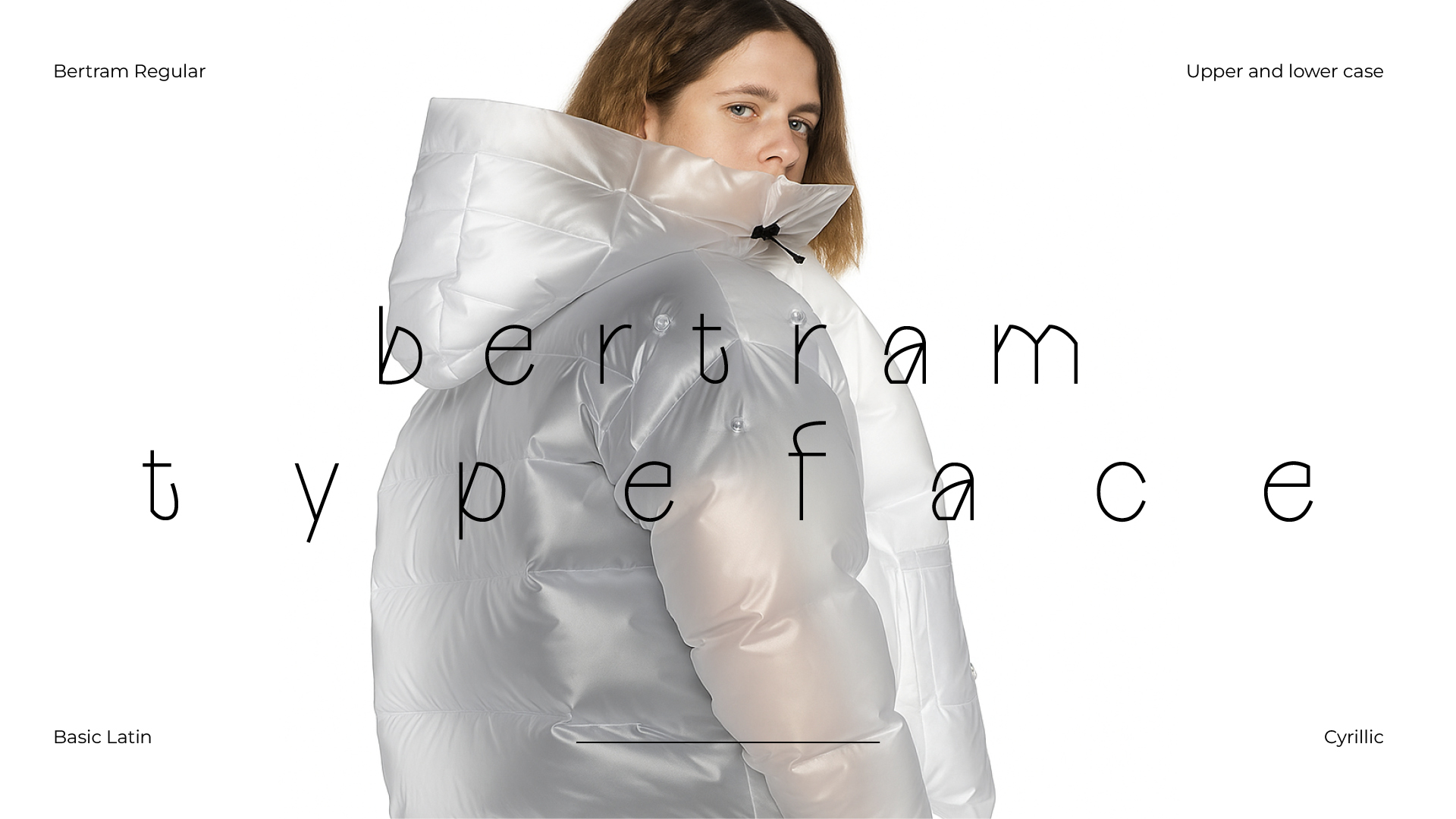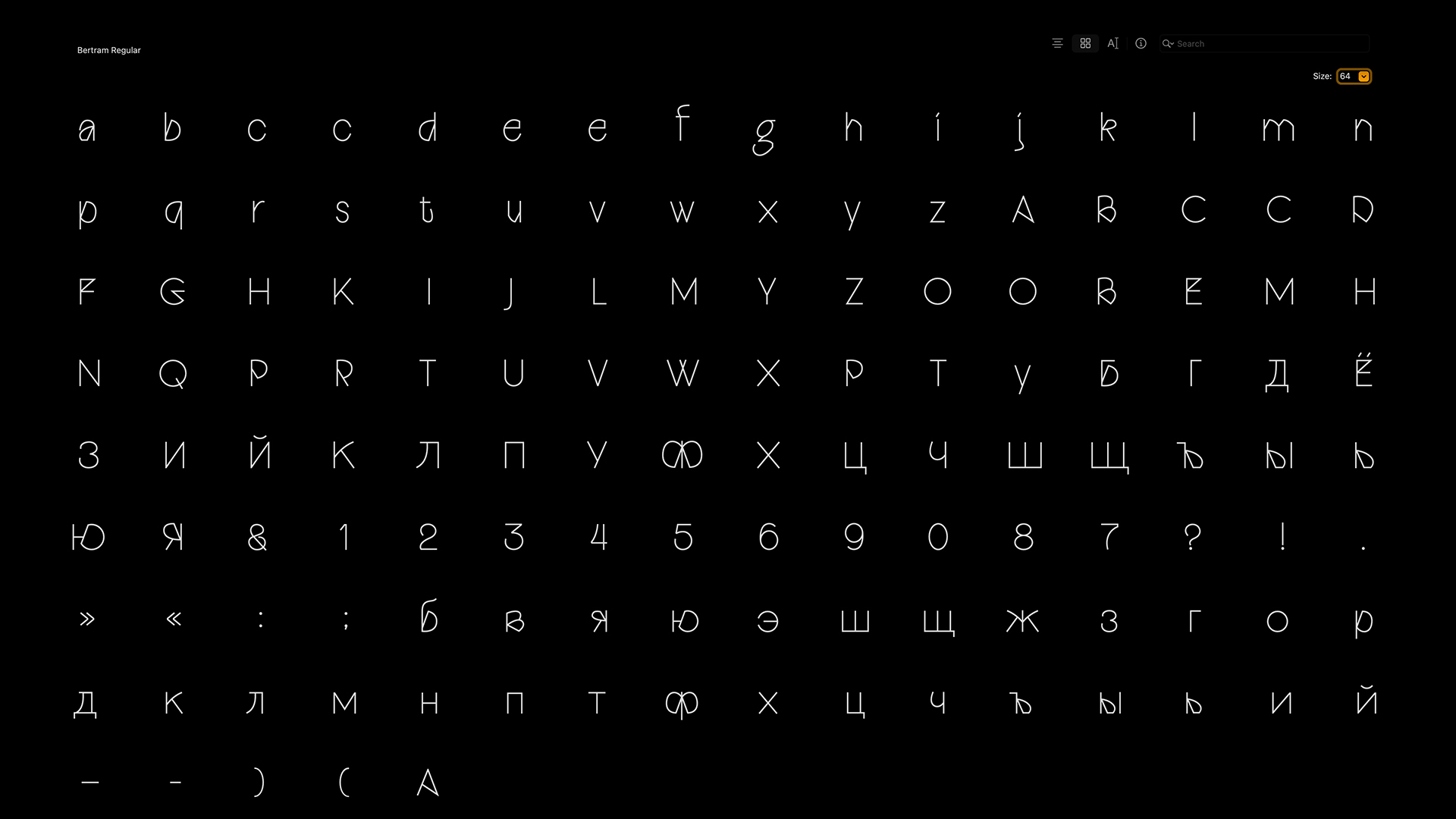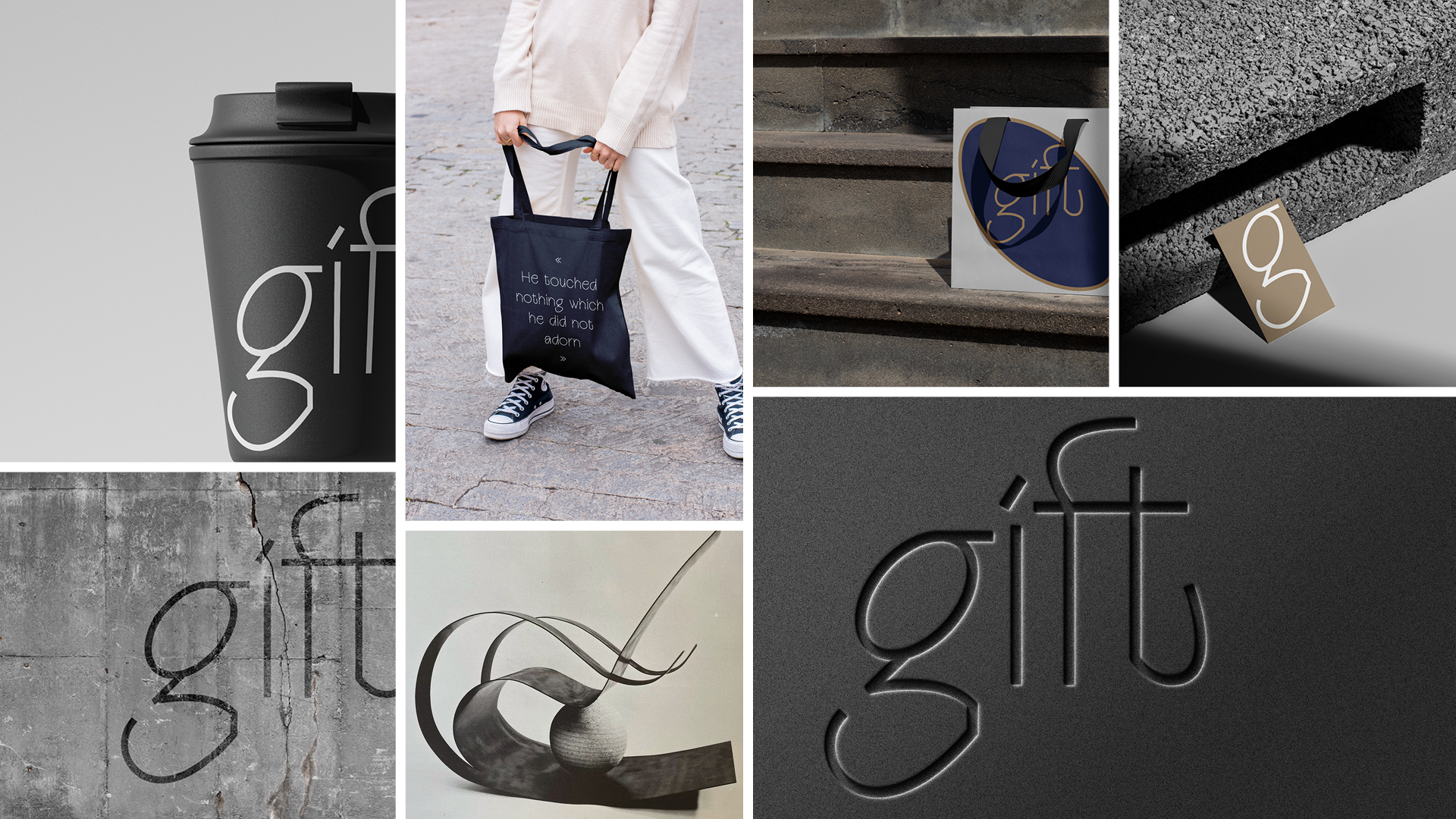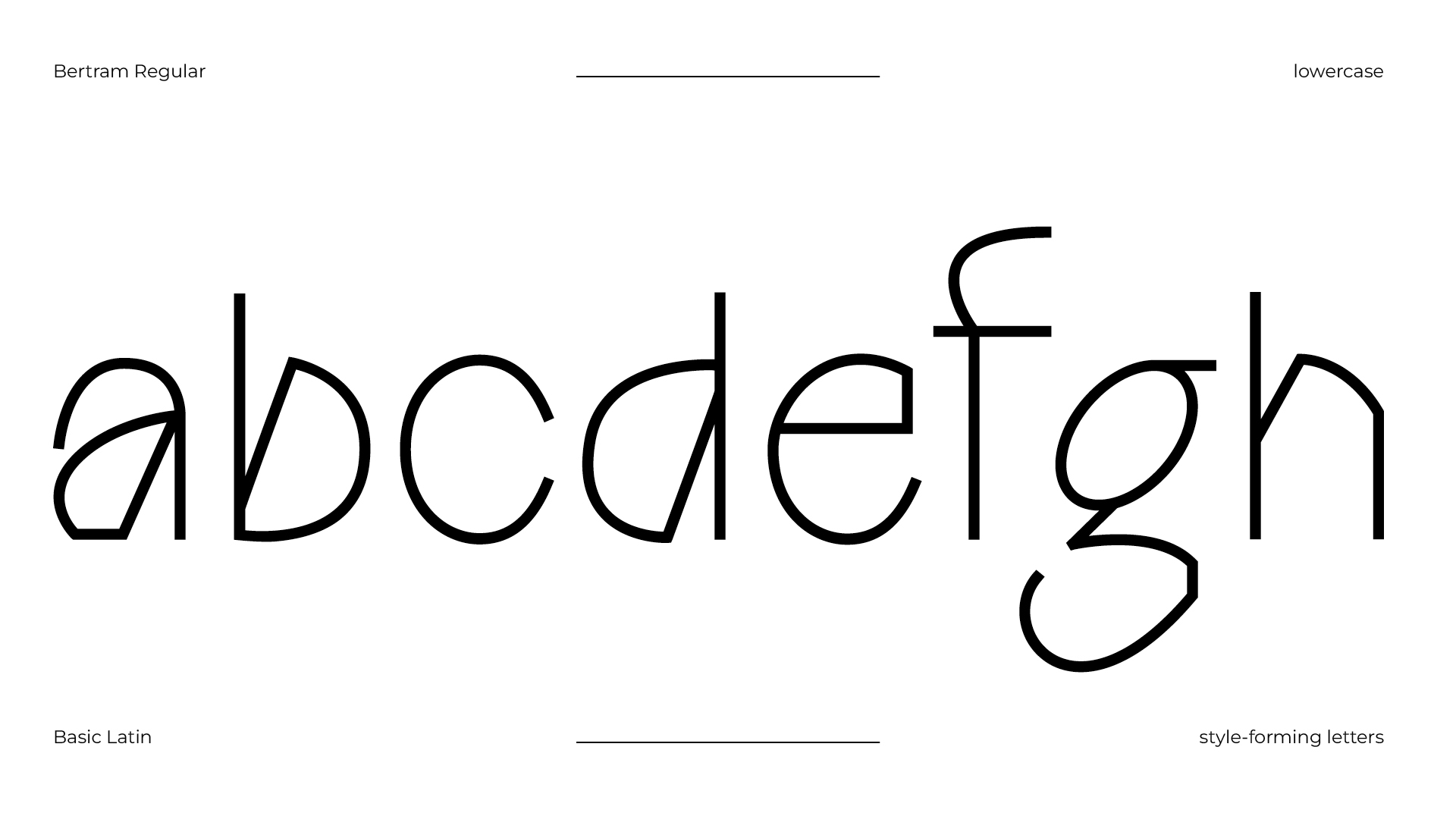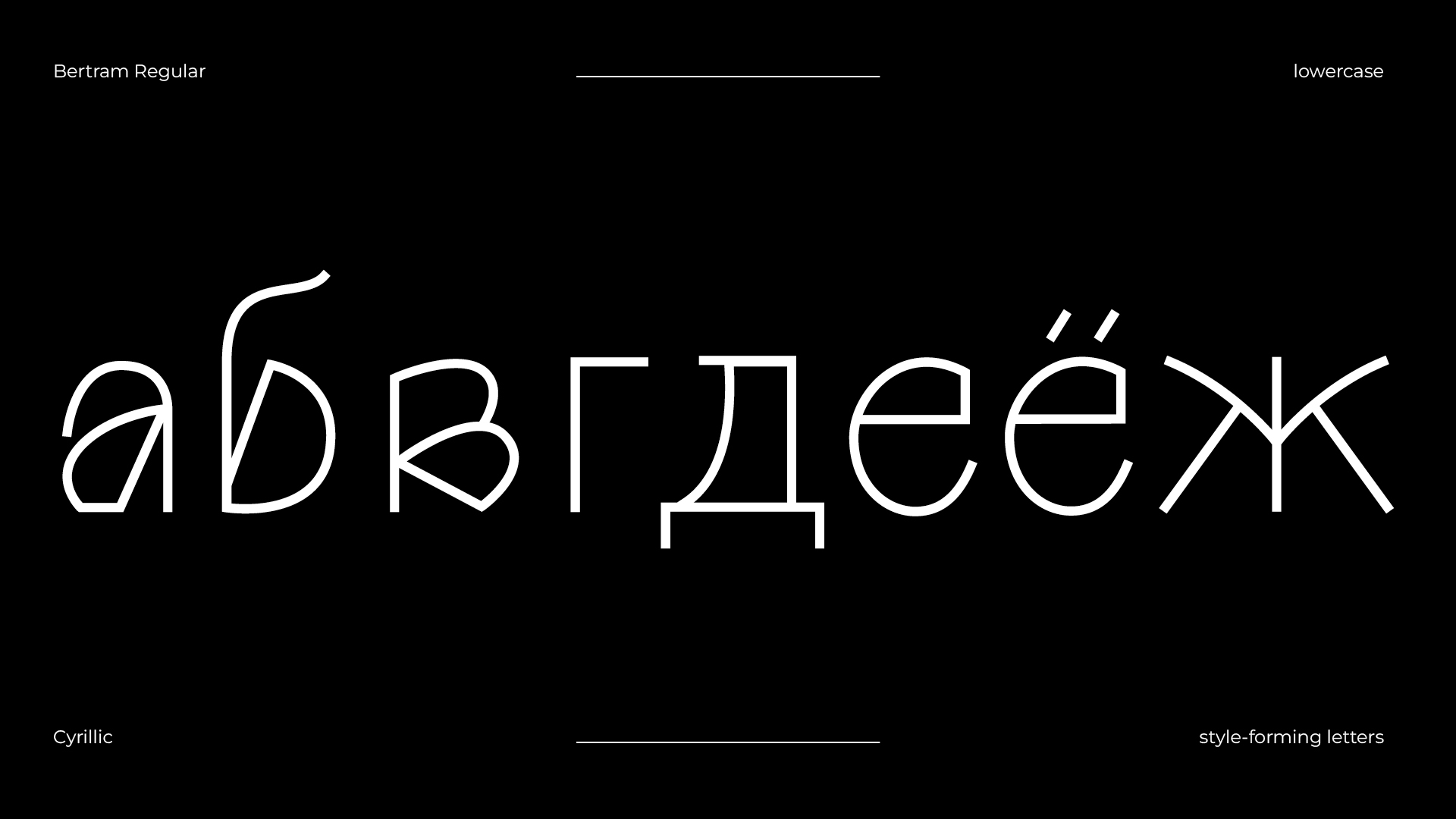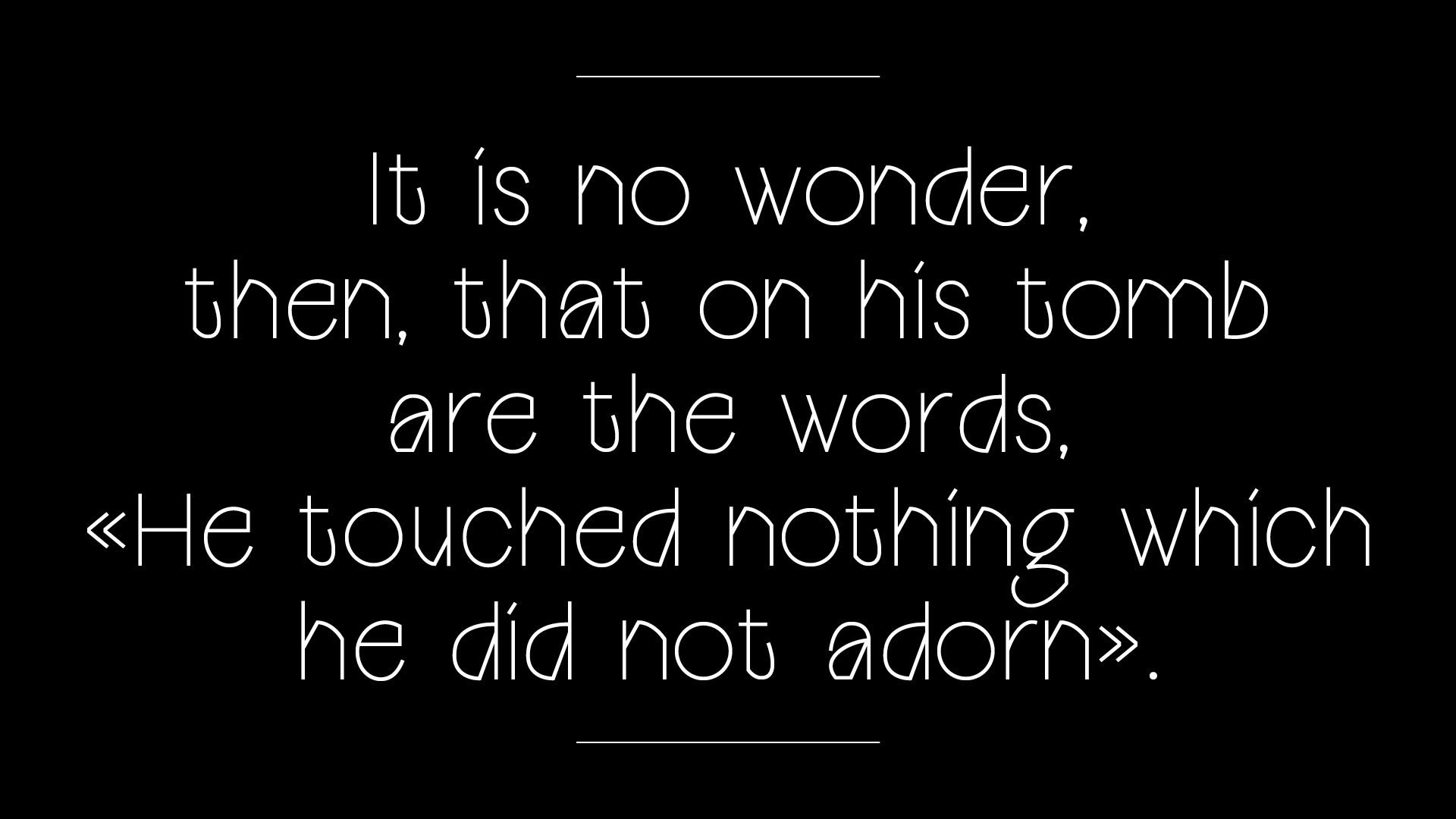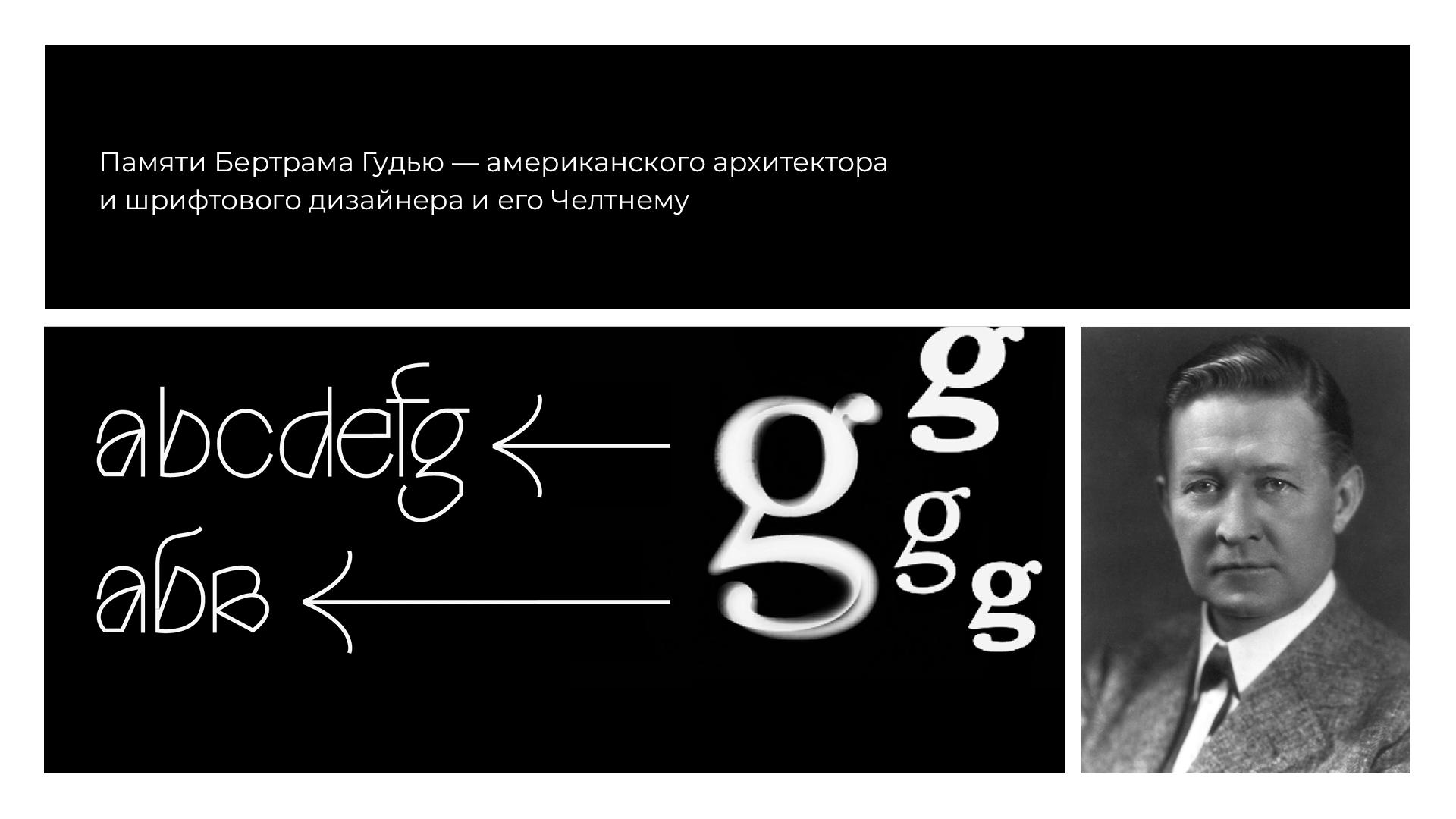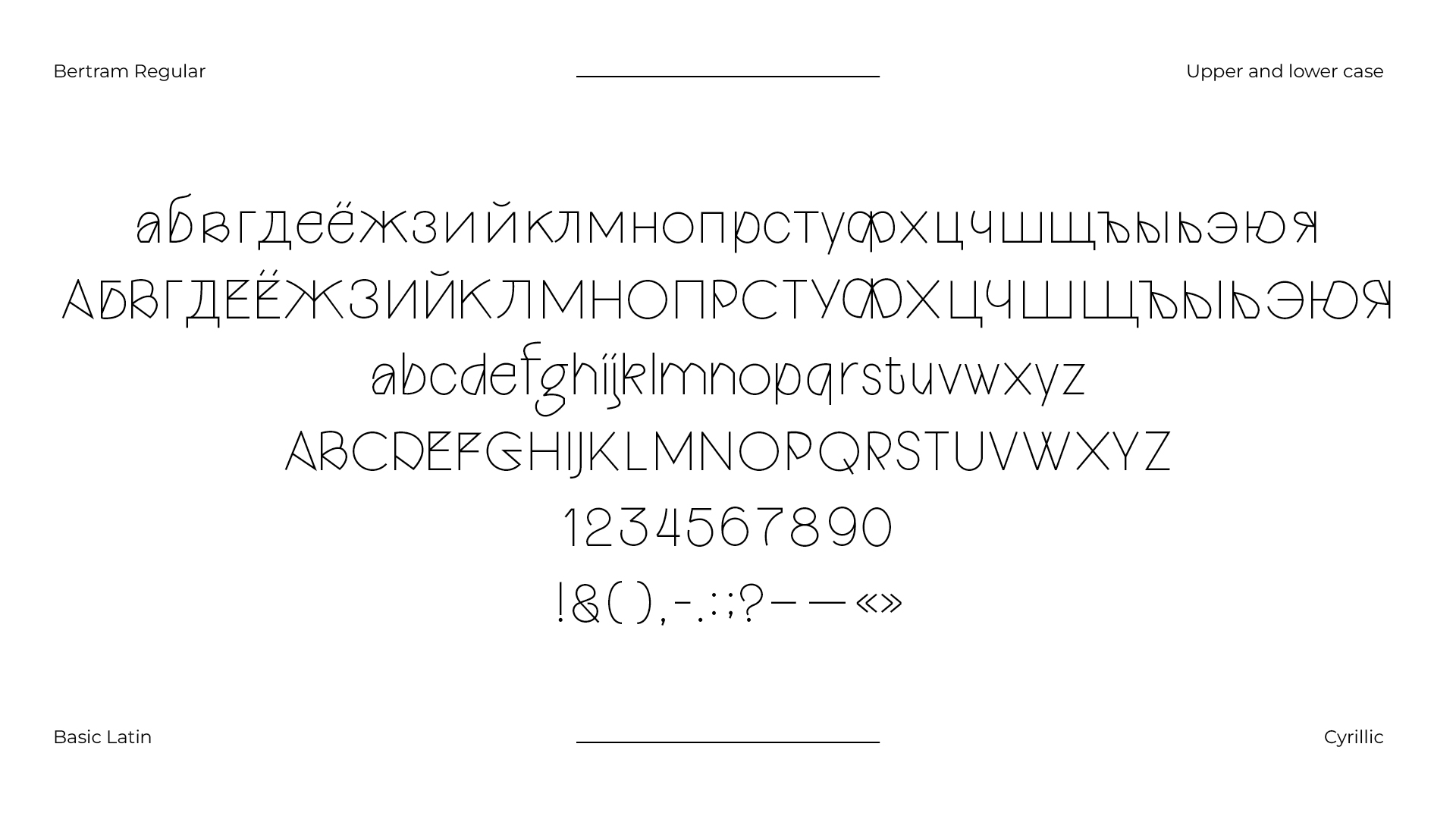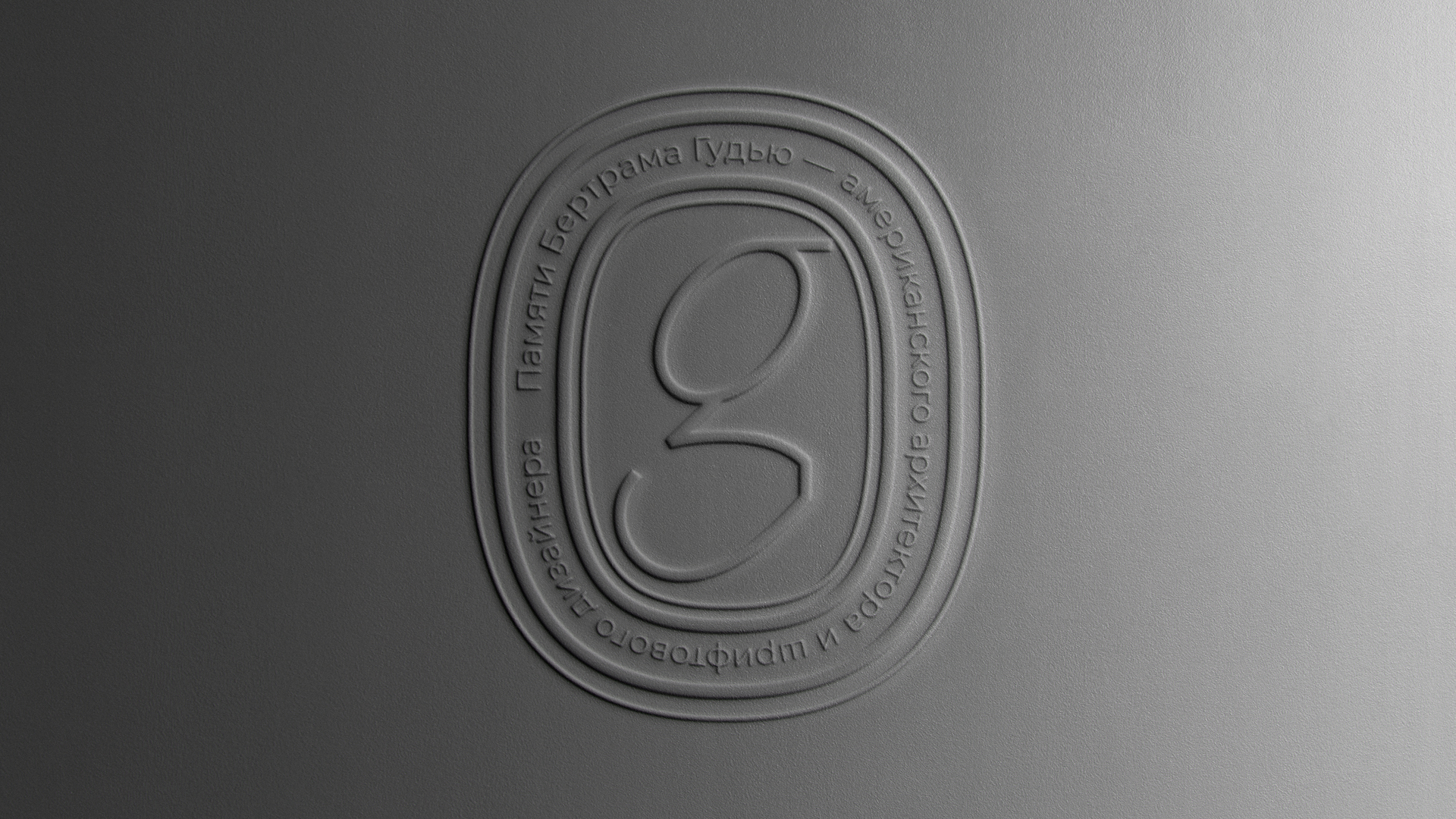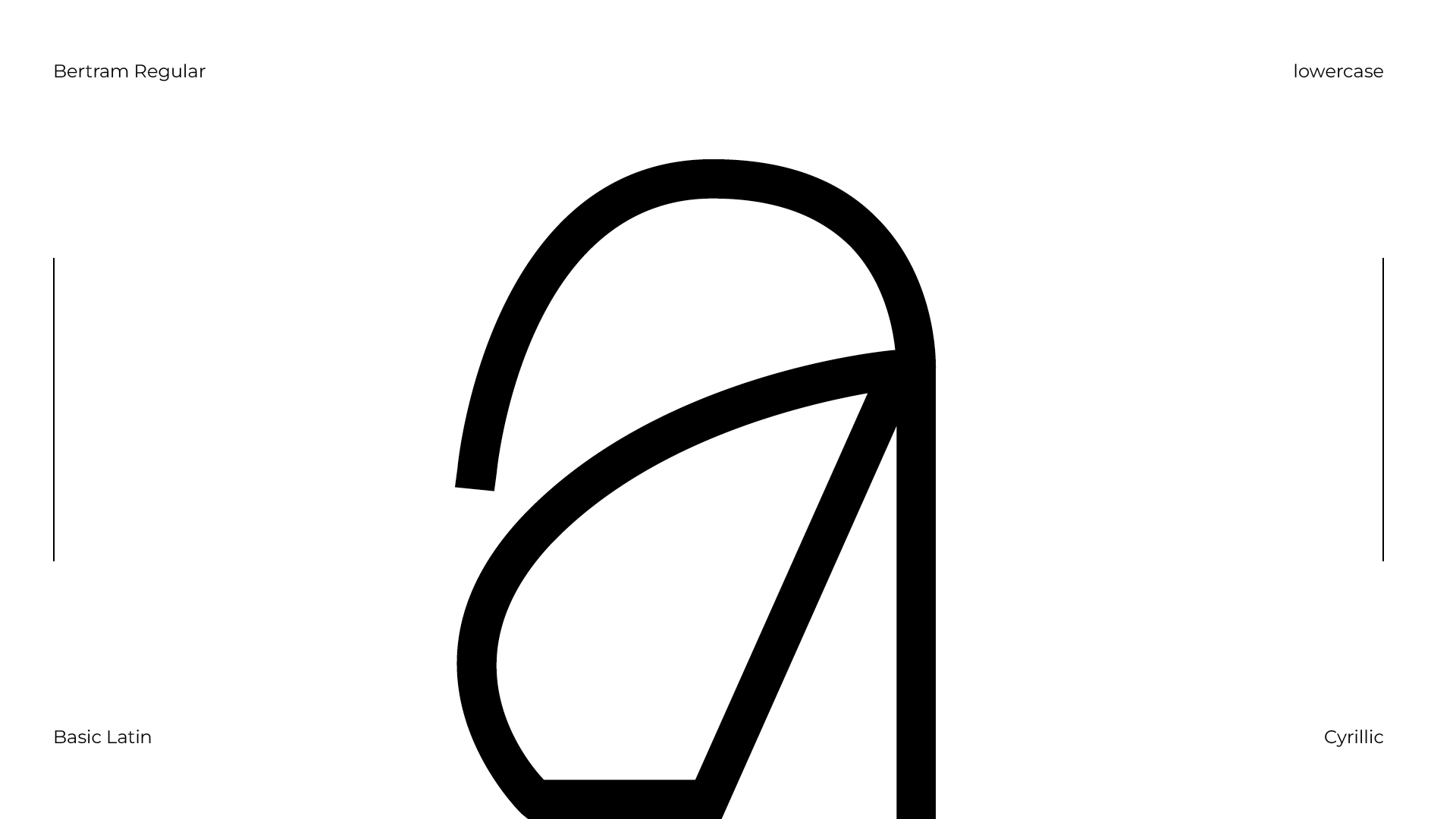
Bertram
Шрифт Bertram разработан в память о великом американском архитекторе и шрифтовом дизайнере Бертраме Гудью. Его шрифт Cheltenham, буква -g-, вдохновили на этот проект. Чтобы понять, насколько важна была для меня буква -g-, нужно обратиться к её особенностям. В Cheltenham она отличается выразительной петлёй и динамичным эффектом, что придаёт шрифту особую характерность и привлекательность. И вот эту самую привлекательность и характерность я хотела отразить во всём шрифте Bertram.